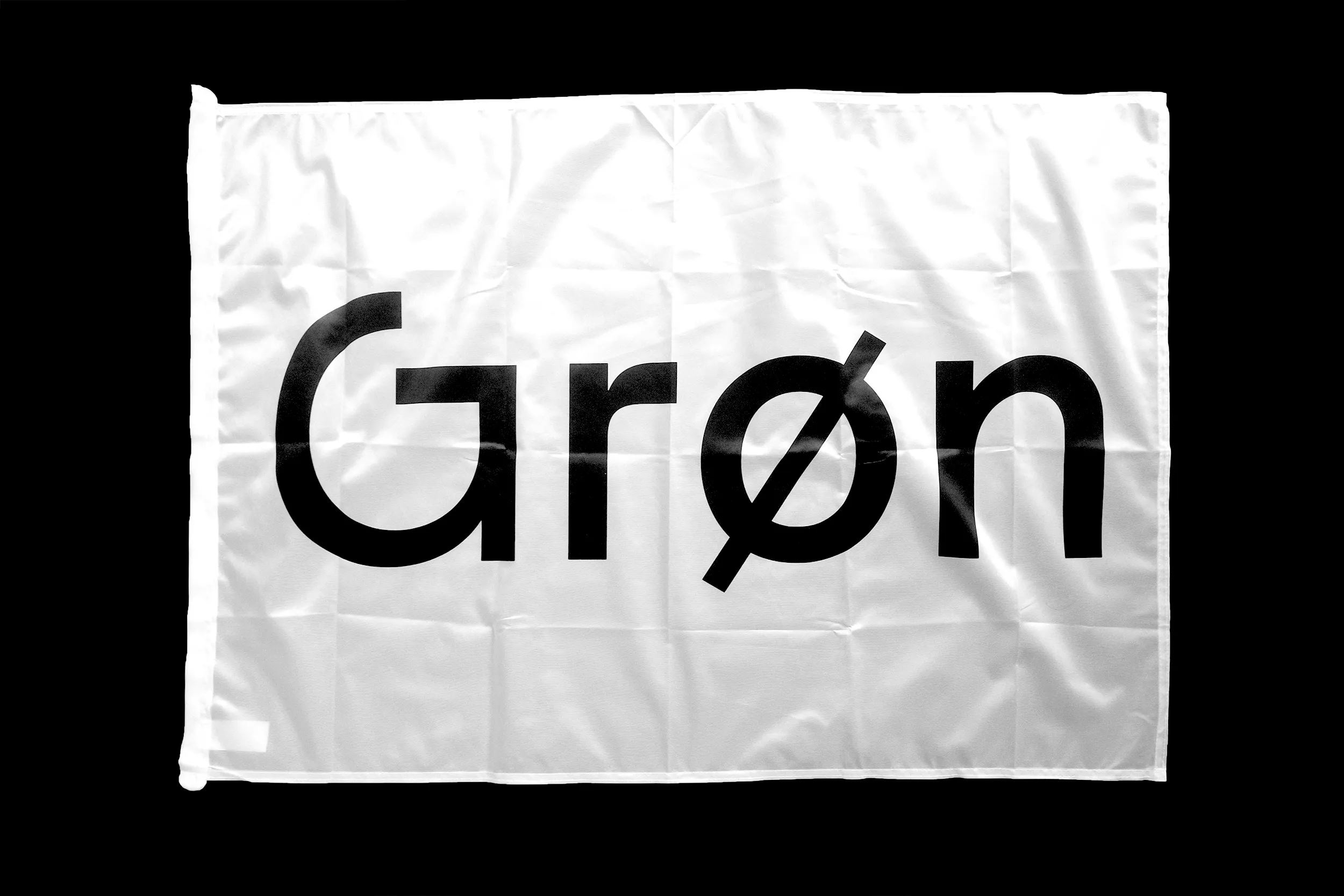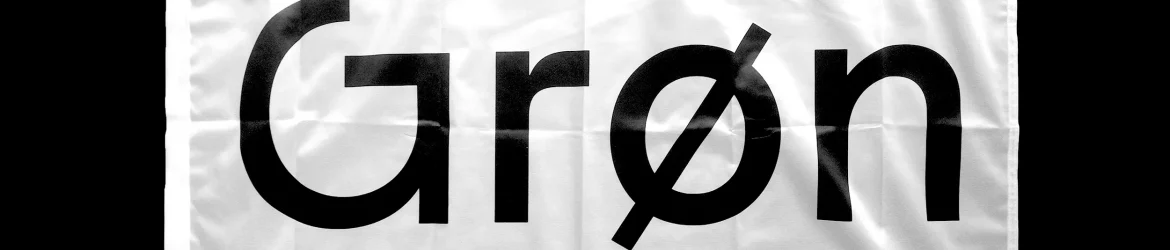
Gronland é uma nova adição à família de fuentes sans serif que oferece um design moderno e contemporâneo para profissionais de design digital. Inspirada nos sistemas de sinalização dos transportes públicos de Nova York e na arquitetura da ilha do Groenlândia, esta fonte foi projetada especialmente para ser utilizada em ambientes digitais e grandes tamanhos. Com oito diferentes pesos variando desde Fine até Black, a Gronland proporciona uma ampla gama de opções para adaptar à qualquer projeto ou contexto. Cada peso contém 750+ caracteres únicos, incluindo as letras do alfabeto latino maiusculas e minúsculas, números e várias formas alternativas, tais como ligaturas estandardizadas e não standardizadas e até mesmo fracionamentos. Com uma paleta de pesos variados, designers podem escolher a opção mais adequada para qualquer projeto sem comprometer o equilíbrio visual do design. A Gronland é uma excelente opção para projetos digitais que exigem um design sólido e moderno, como sites corporativos, aplicativos móveis ou editoriais online. Adquirindo essa fonte de 99designs, você trará a sua criação digital ao nível seguinte – com os atributos únicos da Gronland, seu projeto será impecavelmente profissional, elegante e de alta qualidade.